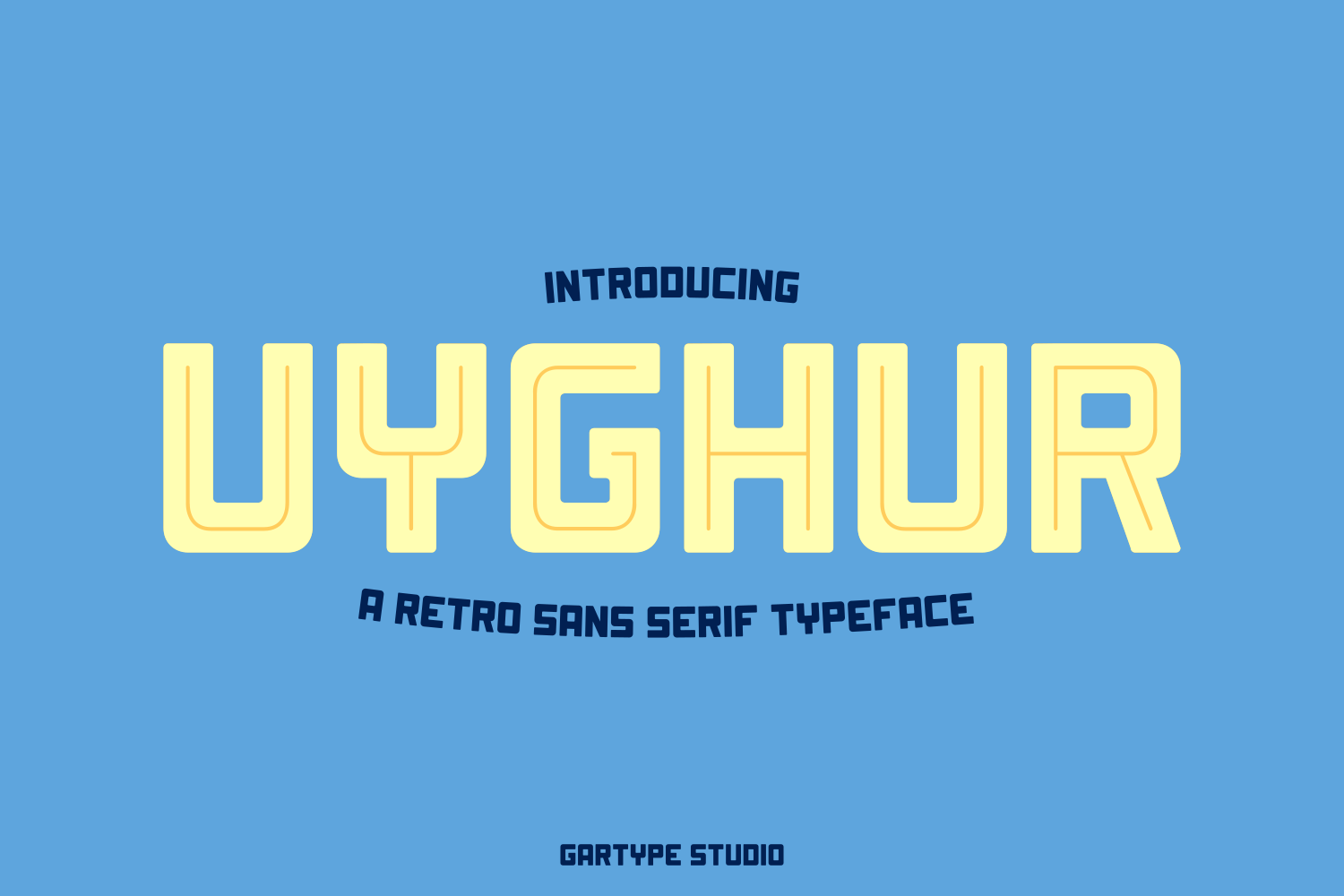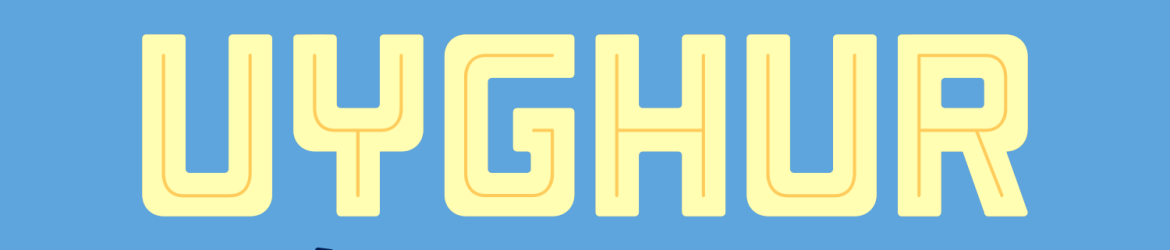
Uyghur Retro Font – Download Grátis
Olá! Introduzimos a Uyghur, uma nova fonte de estilo retro com aparência limpa. Seus três estilos principais – regular, inline e outline – permitem que você personalize suas criações de maneira ainda mais criativa e divertida. Uyghur é perfeitamente adaptável para um vasto range de projetos, desde logotipos até capas de livros em painéis publicitários. Seja para aqueles que valorizam estilos retro modernos ou quem busca algo que traga uma sensação nostálgica a suas produções digitais, Uyghur é o estilo perfeito. A designer Gartype Studio criou esta fonte para se encaixar em várias necessidades de design. Seja para um projeto de marketing, arte publicitária ou até mesmo para decorar seus próprios documentos com um toque único e inovador – Uyghur está aqui para ajudá-lo a encontrar esse equilíbrio perfeito entre modernidade e nostalgia. Para designers que estão sempre à procura de novas opções de fontes, a introdução da Uyghur é uma ótima oportunidade para explorar estilos não tão comuns. Com sua estrutura limpa e seu estilo retro, pode ser usada em qualquer projeto, seja pessoal ou profissional, garantindo que você tenha a capacidade de incorporar uma forte identidade visual em seus trabalhos.
Designer: Gartype Studio